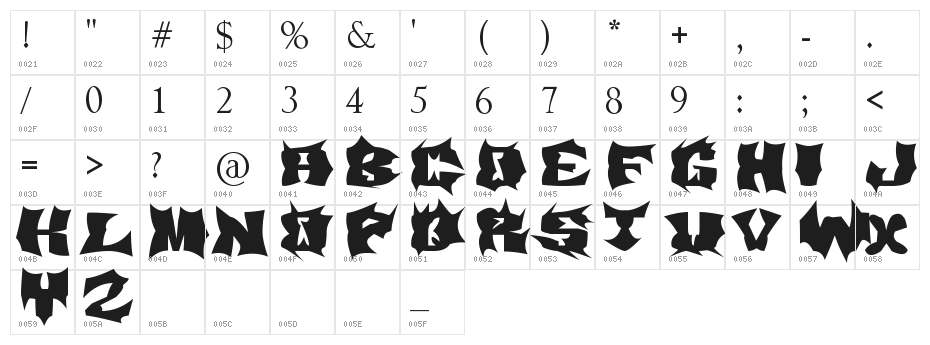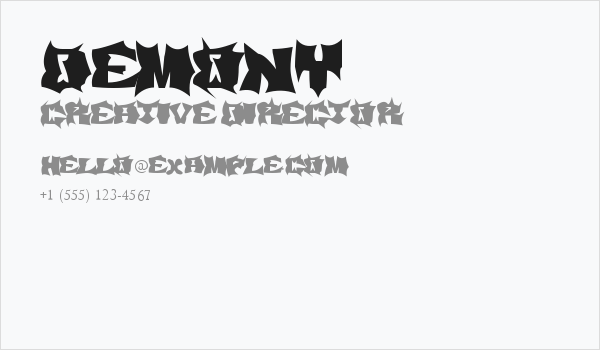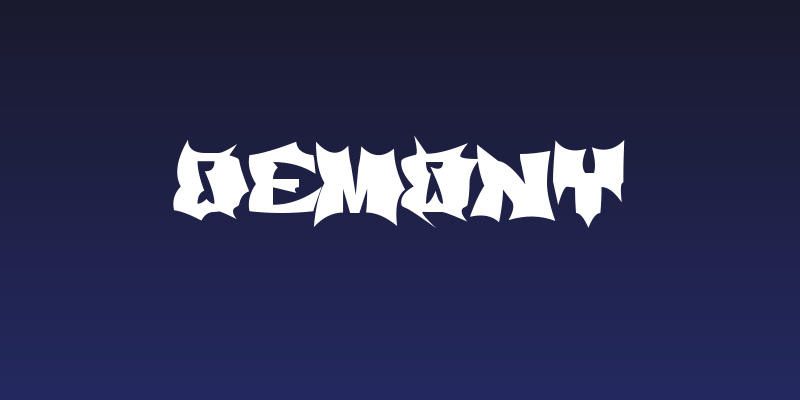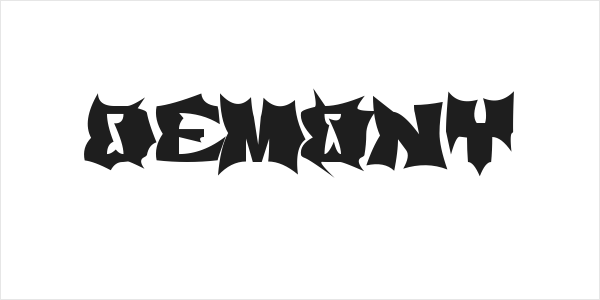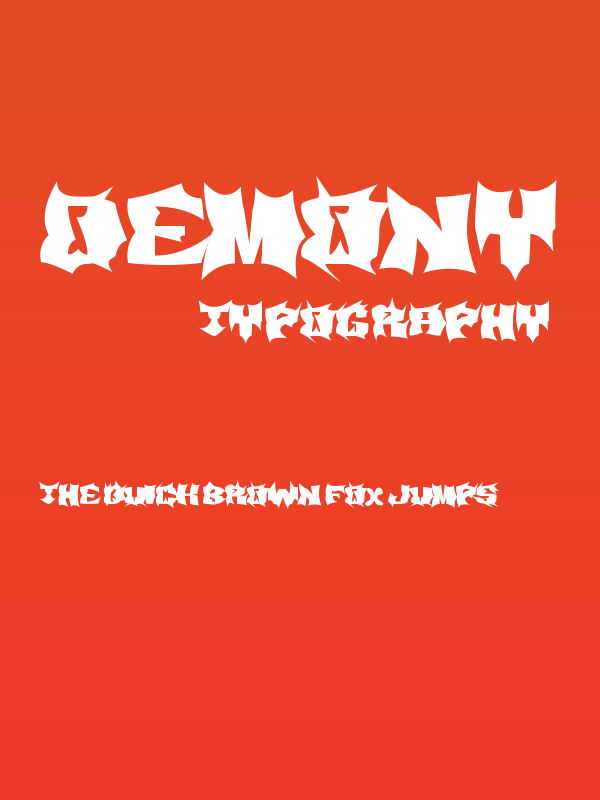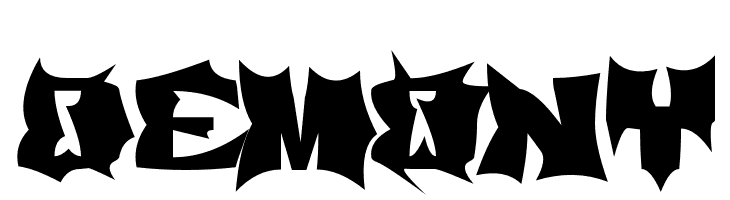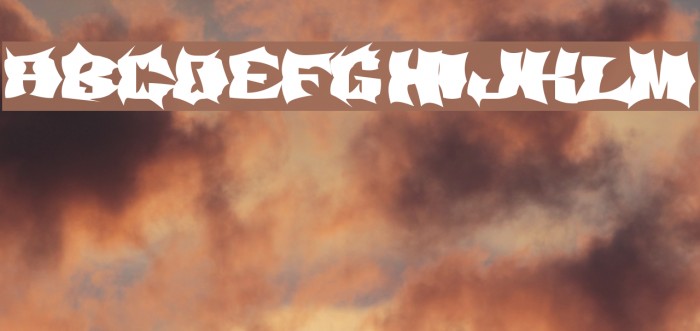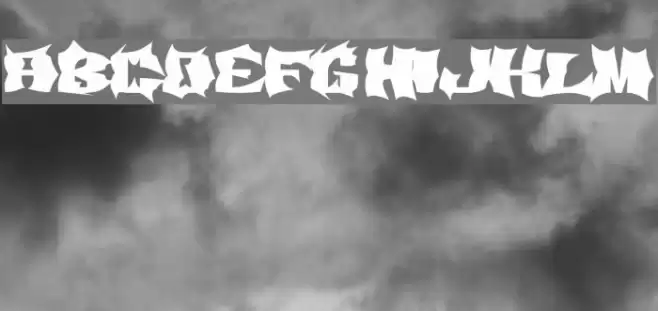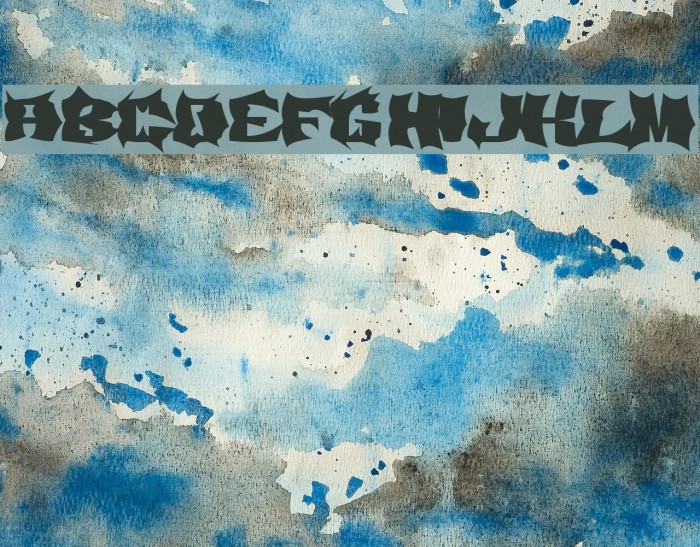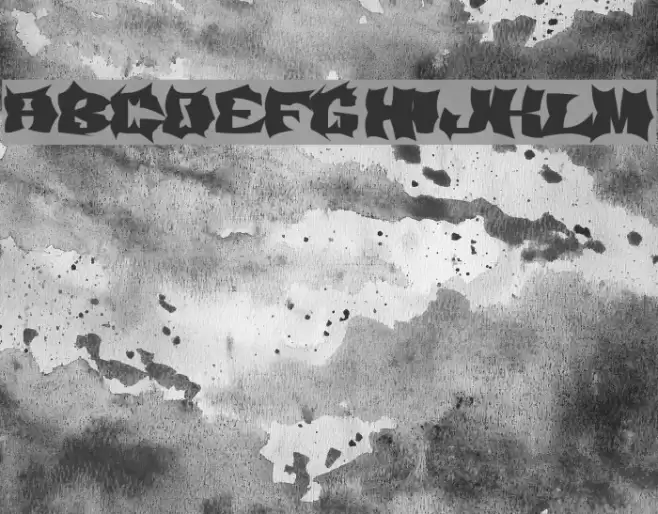
Demony Font
| Estilo general | Modern, Aggressive |
| Proyectos propuestos | Perfect for album covers, posters, video game titles, and branding that requires a strong, edgy aesthetic. |